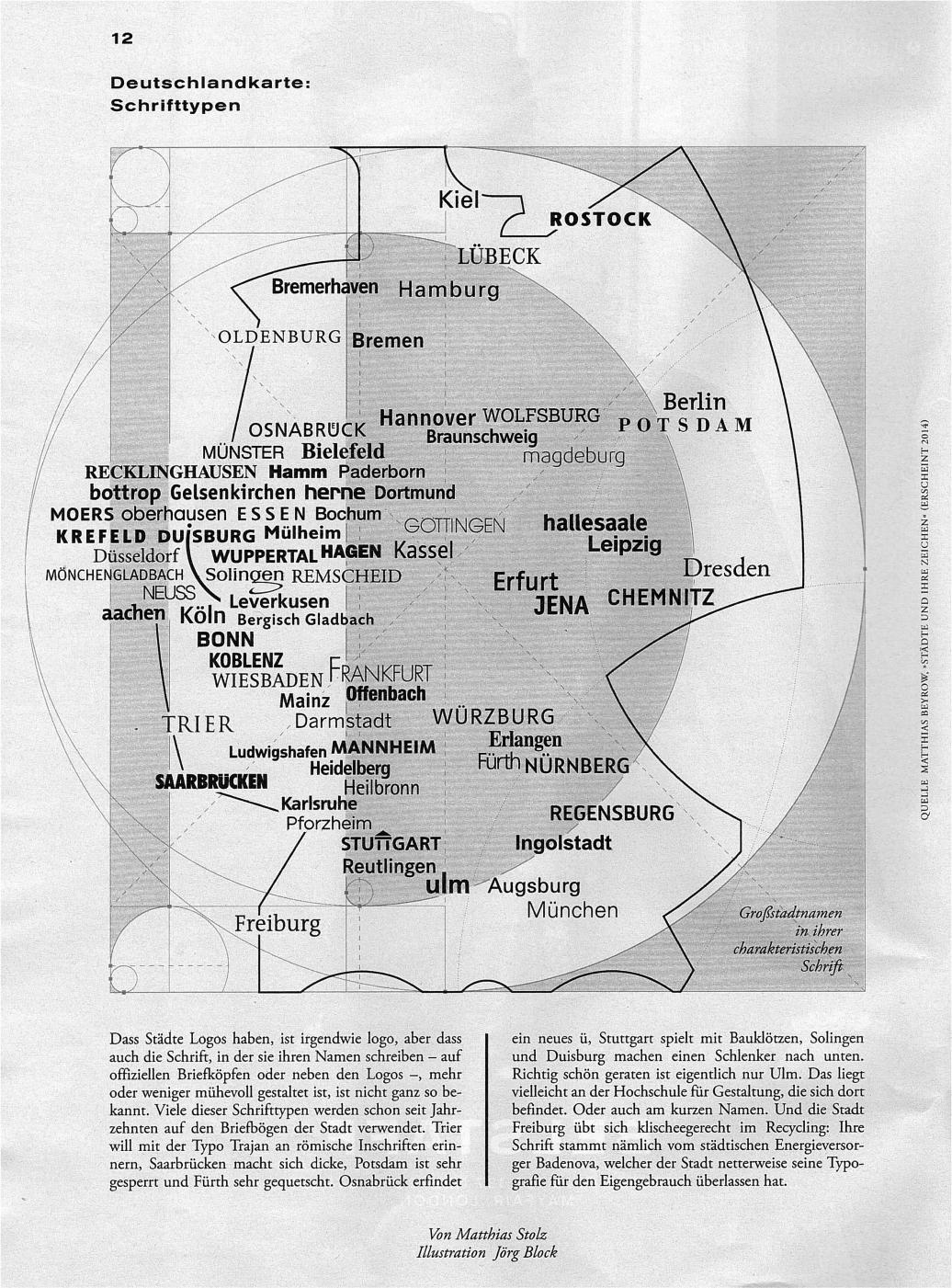
Aus dem aktuelle Zeit Magazin (Nr. 49)
Richtig schön geraten ist eigentlich nur Ulm. Das liegt vieleicht an der hochule für gestaltung, die sich dort befindet.
Befindet? Gibt es die wieder?
Nach Einstellung des Schulbetriebs 1968 und einigen Jahren Leerstand wird das Gebäude der HfG Ulm 1974 an die Universität Ulm vermietet und fortan von den Abteilungen Psychotherapie, Psychosomatische Medizin (Tagesklinik und Ambulanz) sowie dem Institut für Kulturanthropologie genutzt. Infolge der eigentlich zweckentfremdenden Nutzung wird zwangsläufig die Innenarchitektur kleinteiliger, was den ursprünglichen Gebäudecharakter mehr und mehr überformt.
daß es das gebäude noch gibt war schon zu erwarten, aber auch der durschnittliche zeitleser erwartet sicher was anderes wenn er liest von
der hochule für gestaltung, die sich dort befindet
Das beste an dem Artikel ist aber der Deutschland-Umriss, nicht?
Hat was, inklusive D-Hintergrund. Ist das D aus einer bestimmten Schrift?
... wobei ja auf einer kürzlich hier verlinkten Seite (irgendwas mit cutting bei Logos) bestimmt drüber gelästert würde, dass man die Konstruktionslinien janz hipp mit eingebaut hat ... ;-)
Aus dem aktuelle Zeit Magazin (Nr. 49)
Sofern die Logo-Schriften auch Hausschriften sind, wären das auch interessante Infos fürs Wiki. Da gibts eine eigene Rubrik für Städte/Länder/Regionen: